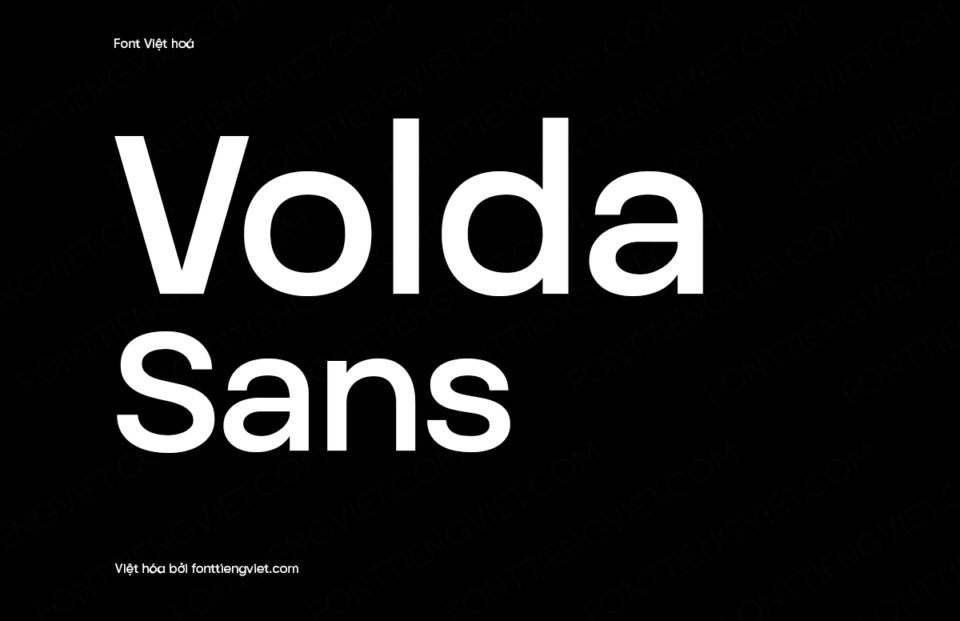
Font Việt hóa 1FTV VIP Volda Sans
Font Việt hóa 1FTV VIP Volda Sans – Bộ phông chữ hiện đại cho thiết kế chuyên nghiệp
Giới thiệu về Font Việt hóa 1FTV VIP Volda Sans trong thiết kế đồ họa
Trong thế giới sáng tạo ngày nay, việc lựa chọn một Font Miễn Phí phù hợp đóng vai trò quan trọng trong việc truyền tải thông điệp của tác phẩm. Font Việt hóa 1FTV VIP Volda Sans nổi lên như một giải pháp tối ưu dành cho những nhà thiết kế đang tìm kiếm sự kết hợp giữa tính hiện đại và sự tinh tế. Đây là một bộ font chữ không chân (Sans Serif) được tinh chỉnh kỹ lưỡng về dấu tiếng Việt, giúp các văn bản trở nên hài hòa và dễ đọc trên mọi nền tảng kỹ thuật số cũng như in ấn. Đặc biệt, đối với các bạn học sinh và giáo viên, bộ phông này mang lại cảm giác trẻ trung, năng động nhưng vẫn giữ được sự chỉn chu cần thiết trong các bài thuyết trình hay tài liệu học tập.
Những đặc điểm nổi bật của Font Việt hóa 1FTV VIP Volda Sans
Cấu trúc hình học chuẩn xác và linh hoạt
Một trong những điểm ấn tượng nhất của Font Việt hóa 1FTV VIP Volda Sans chính là cấu trúc hình học cân đối. Các nét chữ được thiết kế với độ dày vừa phải, tạo nên sự thông thoáng cho văn bản. Sự linh hoạt của bộ font này cho phép nó xuất hiện trong nhiều ngữ cảnh khác nhau, từ các tiêu đề biểu ngữ lớn cho đến những đoạn văn bản nội dung dài mà không gây mỏi mắt cho người xem.
Hệ thống dấu tiếng Việt được tối ưu hóa
Việc sử dụng các phông chữ quốc tế thường gặp lỗi về dấu thanh hoặc khoảng cách chữ khi gõ tiếng Việt. Tuy nhiên, với Font Việt hóa 1FTV VIP Volda Sans, mọi vấn đề này đã được khắc phục hoàn toàn. Các dấu mũ, dấu phụ và dấu thanh được đặt ở vị trí hợp lý, đảm bảo tính thẩm mỹ cao nhất cho ngôn ngữ đặc trưng của Việt Nam. Điều này giúp các bạn học sinh dễ dàng trình bày các dự án học tập một cách chuyên nghiệp nhất.
Ứng dụng thực tế của bộ Font Việt hóa 1FTV VIP Volda Sans
Thiết kế slide bài giảng và tài liệu học tập
Trong môi trường giáo dục, việc trình bày slide đẹp mắt sẽ giúp học sinh tập trung hơn vào nội dung bài học. Sử dụng Font Việt hóa 1FTV VIP Volda Sans cho các tiêu đề chính giúp làm nổi bật trọng tâm kiến thức. Nhờ tính rõ ràng, các em học sinh có thể dễ dàng theo dõi bài giảng ngay cả khi ngồi ở vị trí xa màn hình chiếu. Ngoài ra, phông chữ này còn rất phù hợp để làm các tờ rơi, poster cổ động cho các hoạt động ngoại khóa tại nhà trường.
Xây dựng thương hiệu cá nhân và dự án sáng tạo
Nếu bạn đang bắt đầu xây dựng một kênh blog cá nhân hay làm các dự án thiết kế portfolio, Font Việt hóa 1FTV VIP Volda Sans sẽ là người bạn đồng hành lý tưởng. Với vẻ ngoài thanh lịch, nó giúp định hình phong cách tối giản nhưng sang trọng. Khả năng hiển thị tốt trên cả điện thoại và máy tính khiến người xem có trải nghiệm đọc tốt hơn, từ đó tăng hiệu quả truyền thông cho các sản phẩm sáng tạo của bạn.